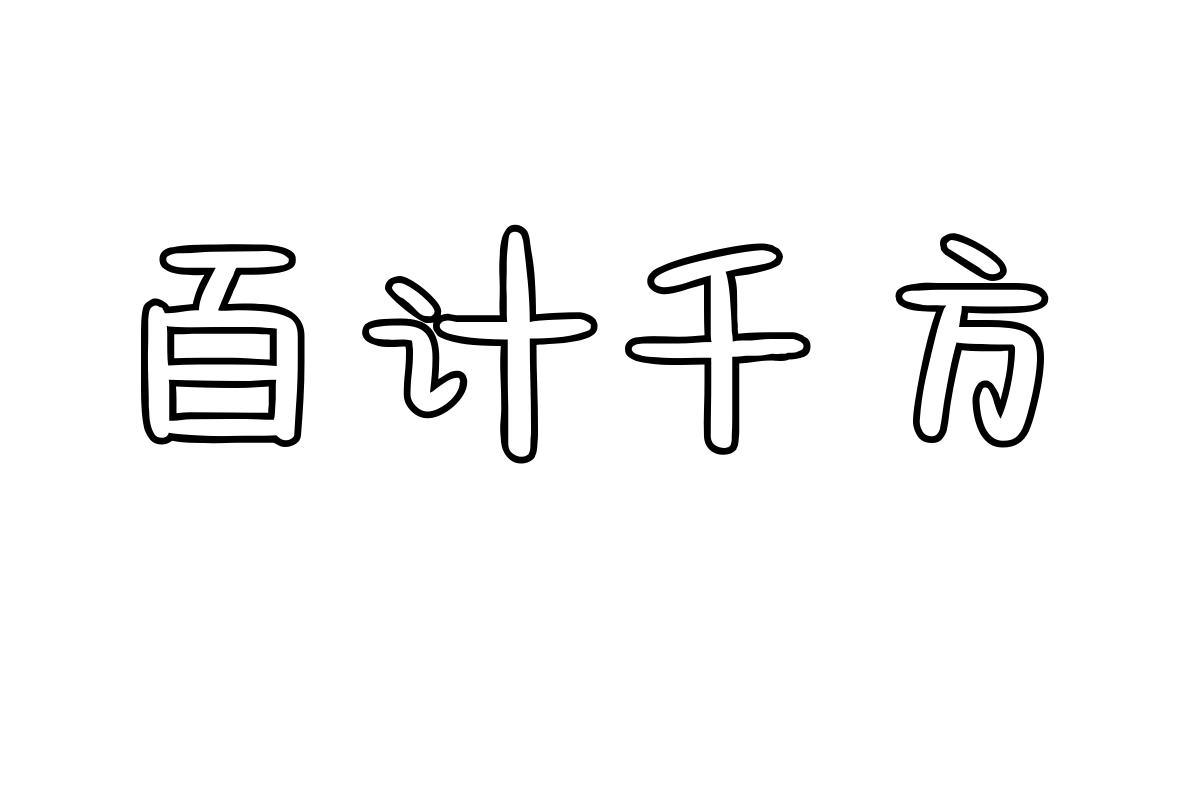
也字工厂可爱描边体是一款由也字工厂设计的字体,它具有可爱的描边效果。这种字体通常用于需要突出显示的文字或标题,以增加视觉吸引力和趣味性。它也适用于儿童书籍、儿童杂志、儿童网站等场景,因为其可爱风格符合儿童的审美需求。
该字体的特点是线条圆润、柔和,给人一种温馨的感觉。它的笔画粗细不一,使得整体视觉效果更加丰富多样。在使用时,可以根据具体需求调整字体大小、粗细、行距等参数,以达到最佳的视觉效果。